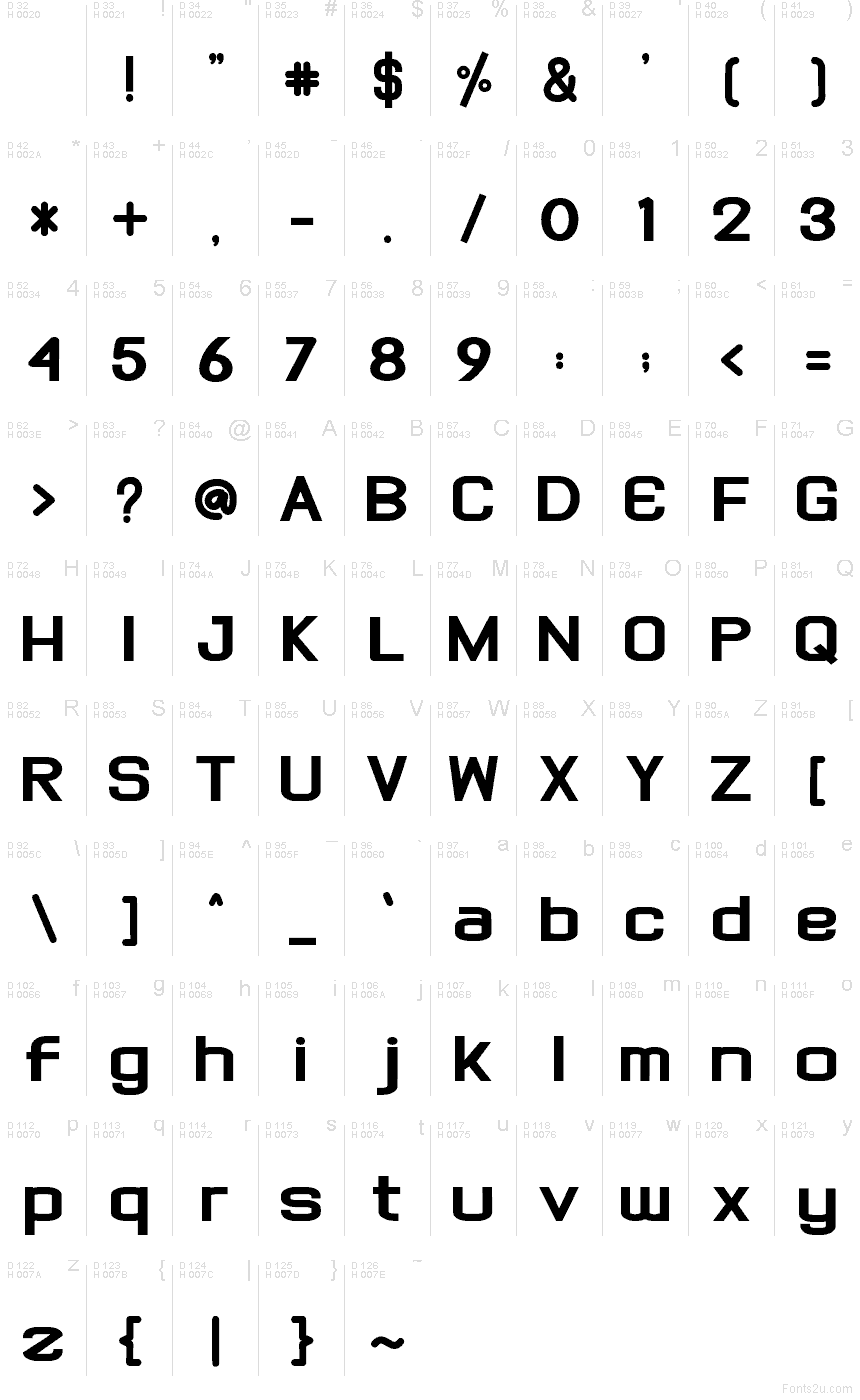
Onsite - Personal Use
Onsite od Letterafa je bezplatné bezpatkové písmo typu display, které definují široké, zaobleně obdélníkové tvary a vyrovnaný rytmus připomínající systémy značení. Písmena působí kompaktně a promyšleně; díky čtvercovým křivkám a plochým řezům získává font hladký, technický vzhled, který nepůsobí jako generická geometrická sans serif.
Tento vizuální styl vynikne v názvech aplikací, tech-brandingu, obalech, výlohách obchodů nebo krátkých plakátových nadpisech, kde kompaktní silueta pomáhá udržet slova pohromadě. Onsite dokáže také ozvláštnit grafiku rozhraní nebo promo akce, zejména pokud hledáte něco měkčího, než je přísně čtvercové bezpatkové písmo, při zachování disciplinovaného a čistého dojmu.